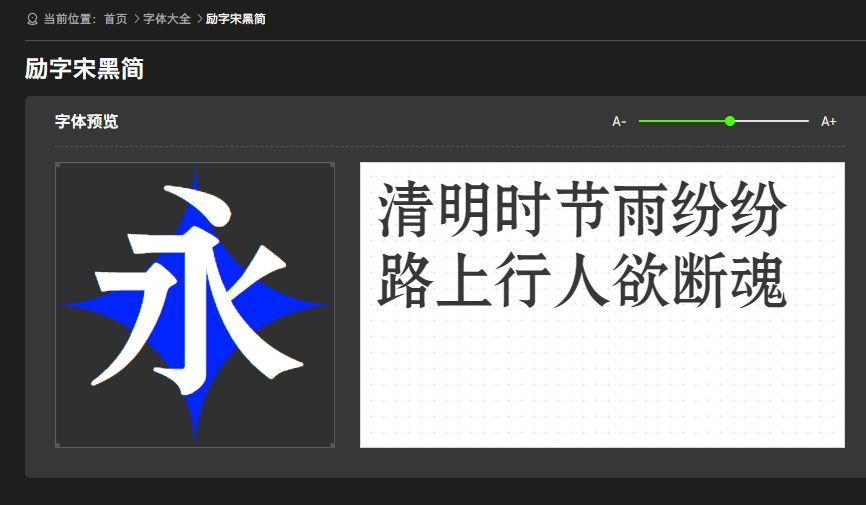
清明时节,这些字体如诗般温暖人心!
清明时节,细雨纷纷,思念如潮。在这个缅怀先祖、感怀时光的节日里,我们除了扫墓祭祖,也有很多品牌方用字体来表达内心的情感。而选择合适的字体,就如同为文字穿上了一件美丽的外衣,让情感更加鲜明、动人。
在这个特殊的时节,我推荐几款温暖人心的字体。首先是“励字宋黑简”,它古朴典雅,仿佛承载着千年的文化底蕴,让人感受到一种历史的厚重感。无论是书写碑文还是撰写祭文,宋体都能展现出一种庄重而又不失温馨的氛围。
另一款值得推荐的字体是“云书法硬笔颜楷简”,它线条流畅、结构匀称,给人一种清新自然的感觉。在清明时节,用楷体书写一首缅怀先人的诗歌,不仅能够表达深情,还能让人感受到一种宁静与和谐。
在这个充满思念与感怀的节日里,选择合适的字体,让文字成为我们情感的载体,传递出我们对先人的敬意与怀念。愿这些温暖的字体,如诗般陪伴我们度过一个难忘的清明节。